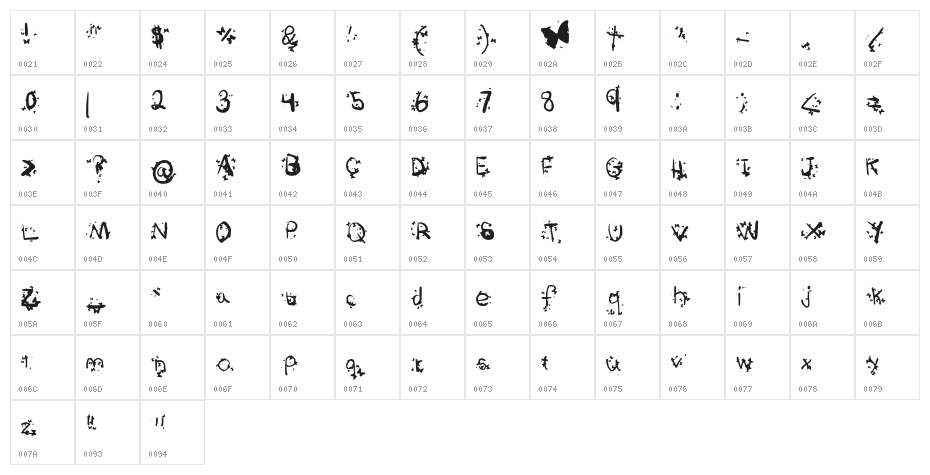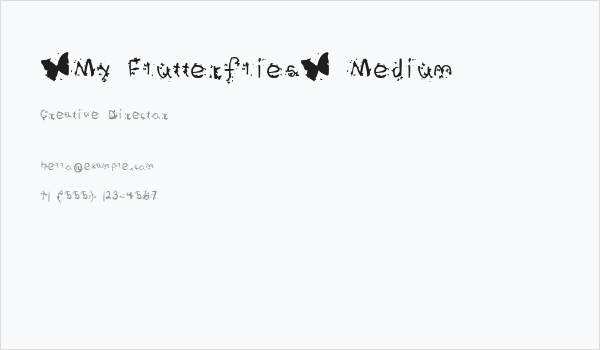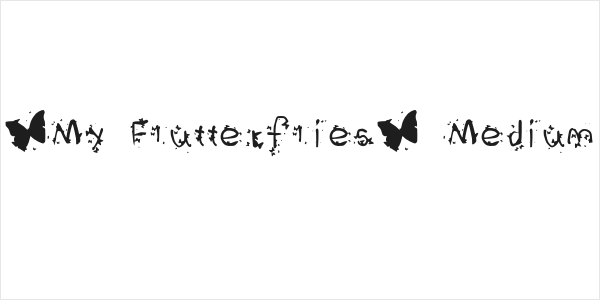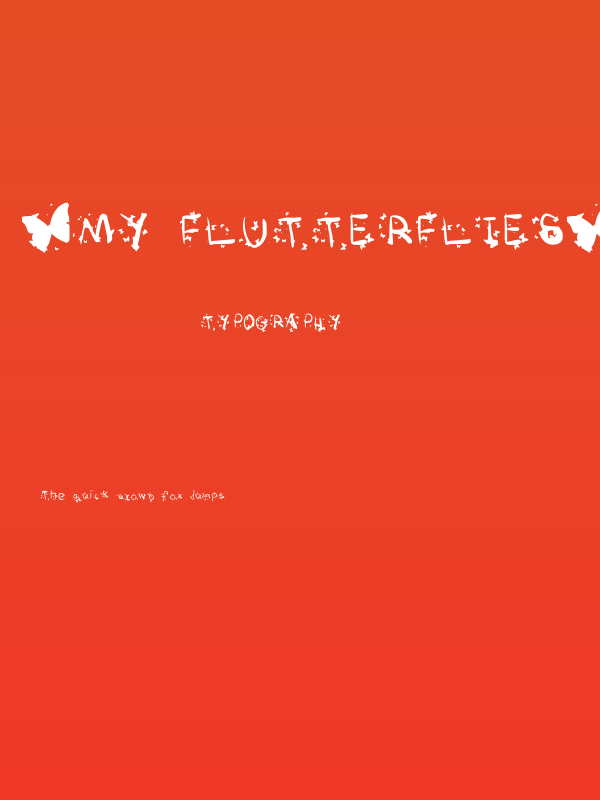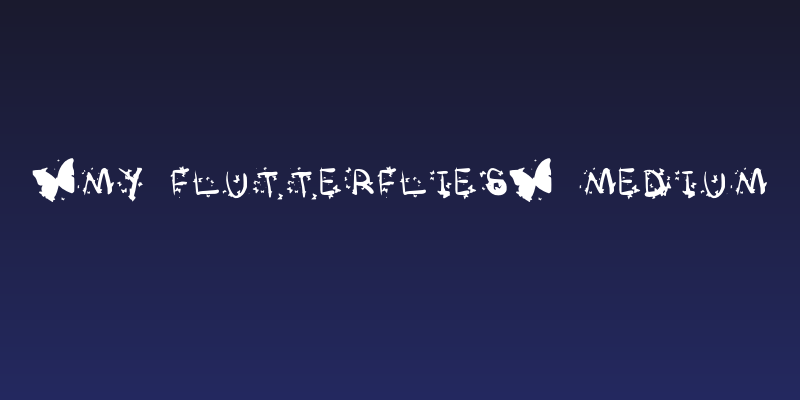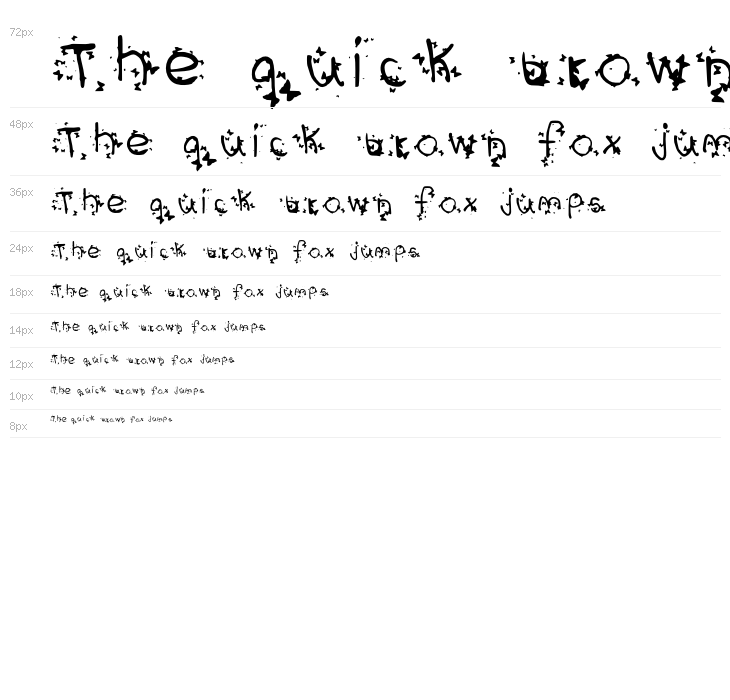
*My Flutterflies* Medium Font
| Caso d'uso | Headlines, Logos, Artistic projects |
| Progetti proposti | Ideal for nature-themed designs, children's book covers, creative invitations, and whimsical branding projects. |